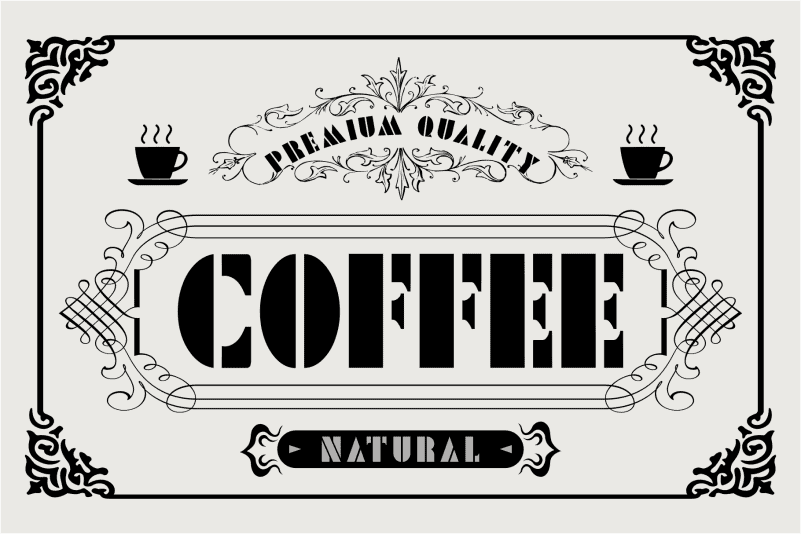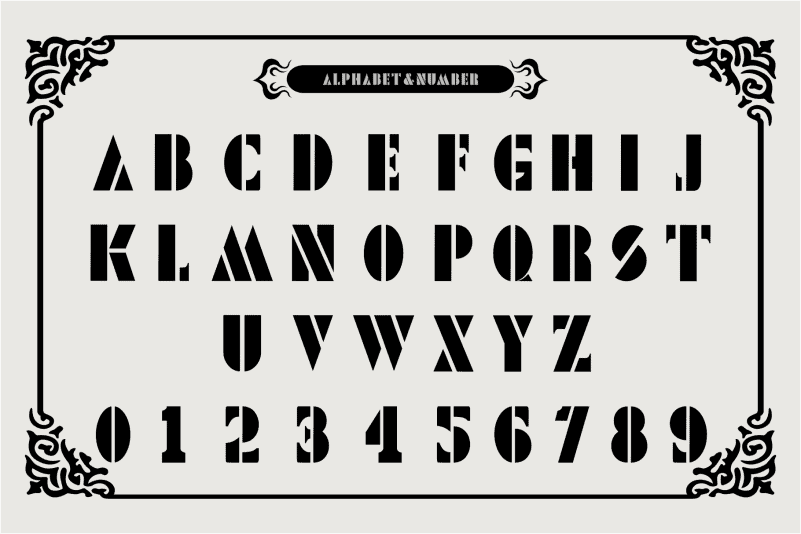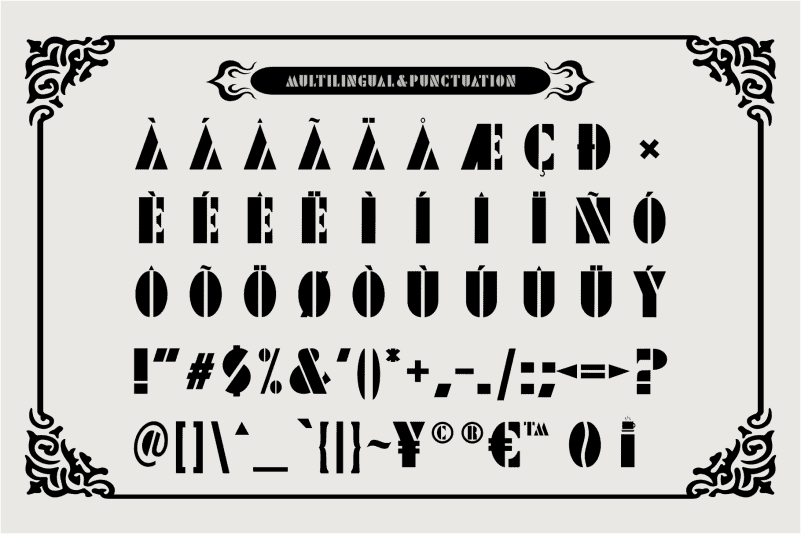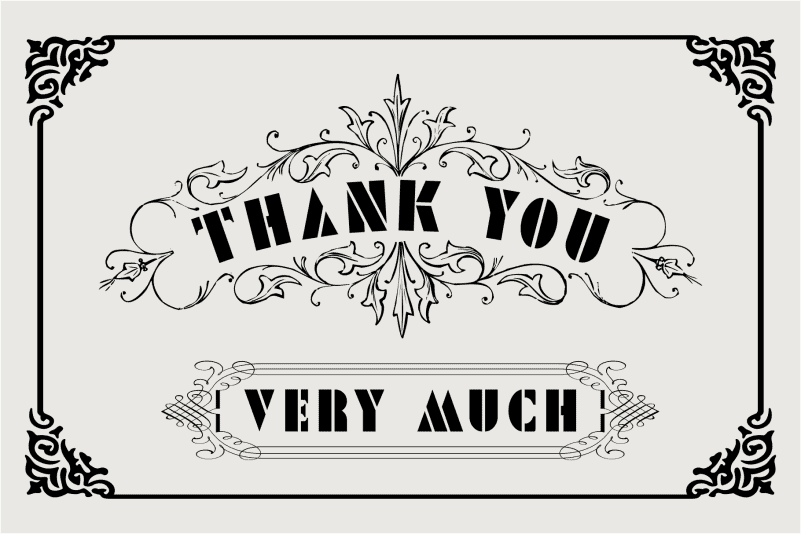
Ngopi Display Font
Ngopi Display Font , adalah font tampilan yang bagus. Ini menampilkan gaya unik yang membuatnya sempurna untuk desain apa pun yang membutuhkan tampilan perkotaan. Ini akan meningkatkan berbagai proyek desain ke tingkat tertinggi, baik itu branding, heading, desain pernikahan, undangan, tanda tangan, logo, label, dan banyak lagi!
Ini berisi huruf besar, huruf kecil, multibahasa, angka dan simbol, tanda baca & PUA yang dikodekan